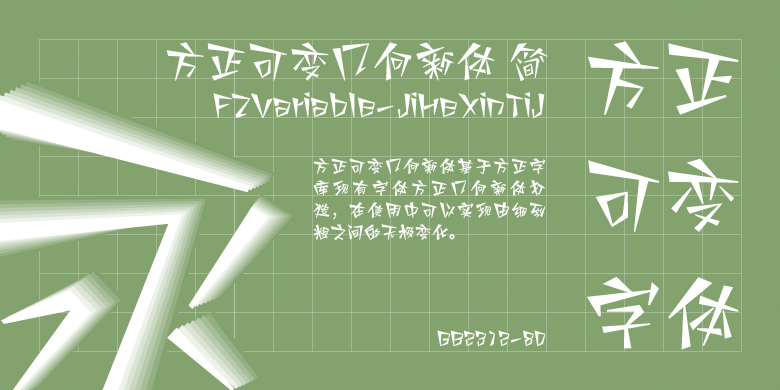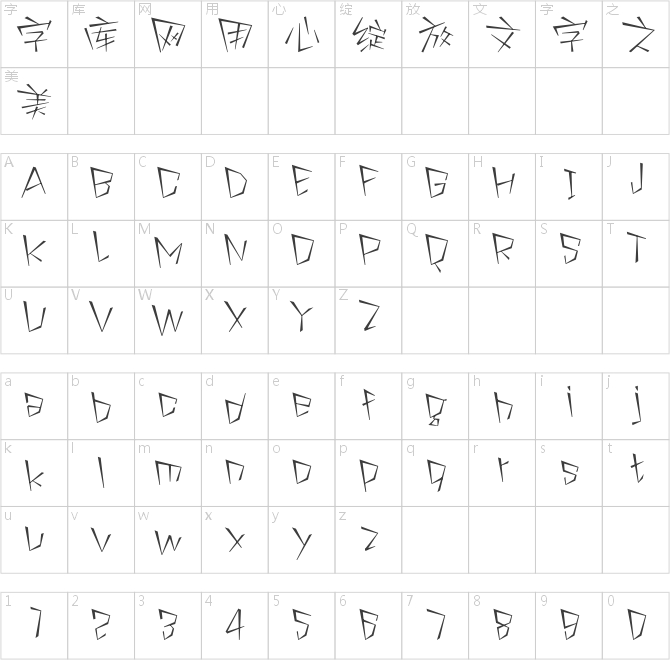
方正可變幾何新體 簡 詳情頁
字體名稱: 方正可變幾何新
方正可變幾何新體支持文字粗細無級調節,設計師通過調整字重軸(Weight)的變化,可以實現字形的平滑連續的細微調整,滿足不同版式的設計需求。 該字體主要以幾何形組成樣式,以多邊形為主要結構,字體風格飄逸隨性,整體視覺效果搶眼,穩重又不失趣味,單個字體看又別具一格,字體意在創新。